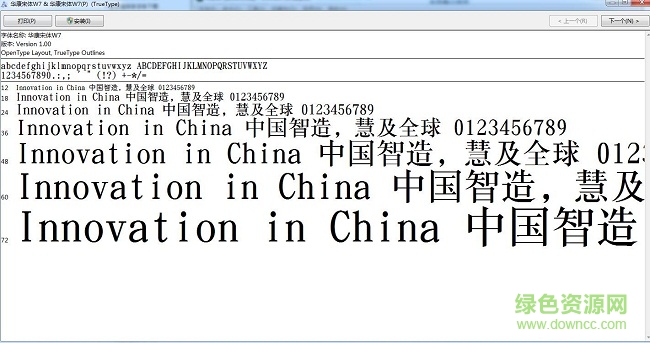
dfpsongw7是什么字體?dfpsongw7字體又叫華康宋體W7,這款字體格式為ttf,在古代,宋體常常用于雕版印刷;在現(xiàn)代,一般的文章排版也都是采用宋體,需要的朋友快來(lái)下載使用吧!
爽快明朗的宋體,自傳統(tǒng)木刻板的風(fēng)格而來(lái),橫、縱筆劃間比例分明,筆畫(huà)末端有裝飾性的襯線,規(guī)范化的筆形是為古代工匠們方便雕字的文化遺跡。宋體擁有相當(dāng)高的閱讀性,適合于內(nèi)文使用。
宋體字始于明弘治年間蘇州地區(qū) 后曾通行日本、朝鮮和越南等國(guó)家。明代中期所形成的“線裝書(shū)”如今是古籍的代名詞。同時(shí)期所形成的宋體字也發(fā)展演變成今天最常用、最規(guī)范的印刷體漢字。